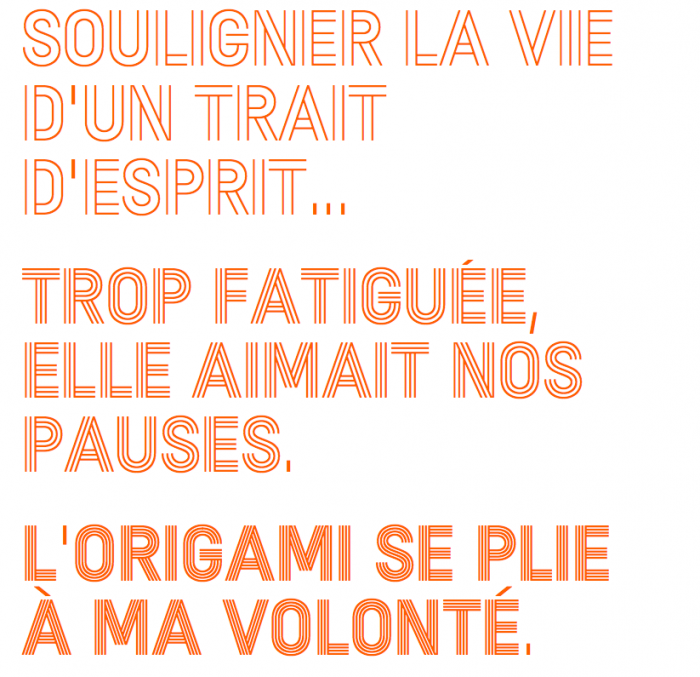
Suche Schrift „PARADE“ oder ähnliche Schrift
Hallo, seit einer Weile recherchiere ich Multi-Line-Schriften und diese hier  „PARADE“ habe ich in meine Herz geschlossen. Die modulare Logik der einzelnen Schnitte bei konstanter Breite der Einzelinien ist faszinierend. Es geht mir vor allem um die linierten Versionen. Diese haben eine Brechung bzw. Faltung in den Linienbänder. Es gibt entfernt ähnlichen Schriften, aber eben immer mit zwei relevanten Unterschieden. Entweder sind
1. „A“ und „E“ oben rund und die Linienbänder sind nicht gefaltet bzw. gebrochen (z.B. Gala oder Pentaprism) oder
2. es gibt nur einen einzigen Schnitt mit eher vielen Linien in 70er-Anmutung, aber eben keine Schriftfamilie (z.B. Trilium).
— Habt ihr irgendwo  eine solche Schrift mit den Merkmalen der Parade gesehen?